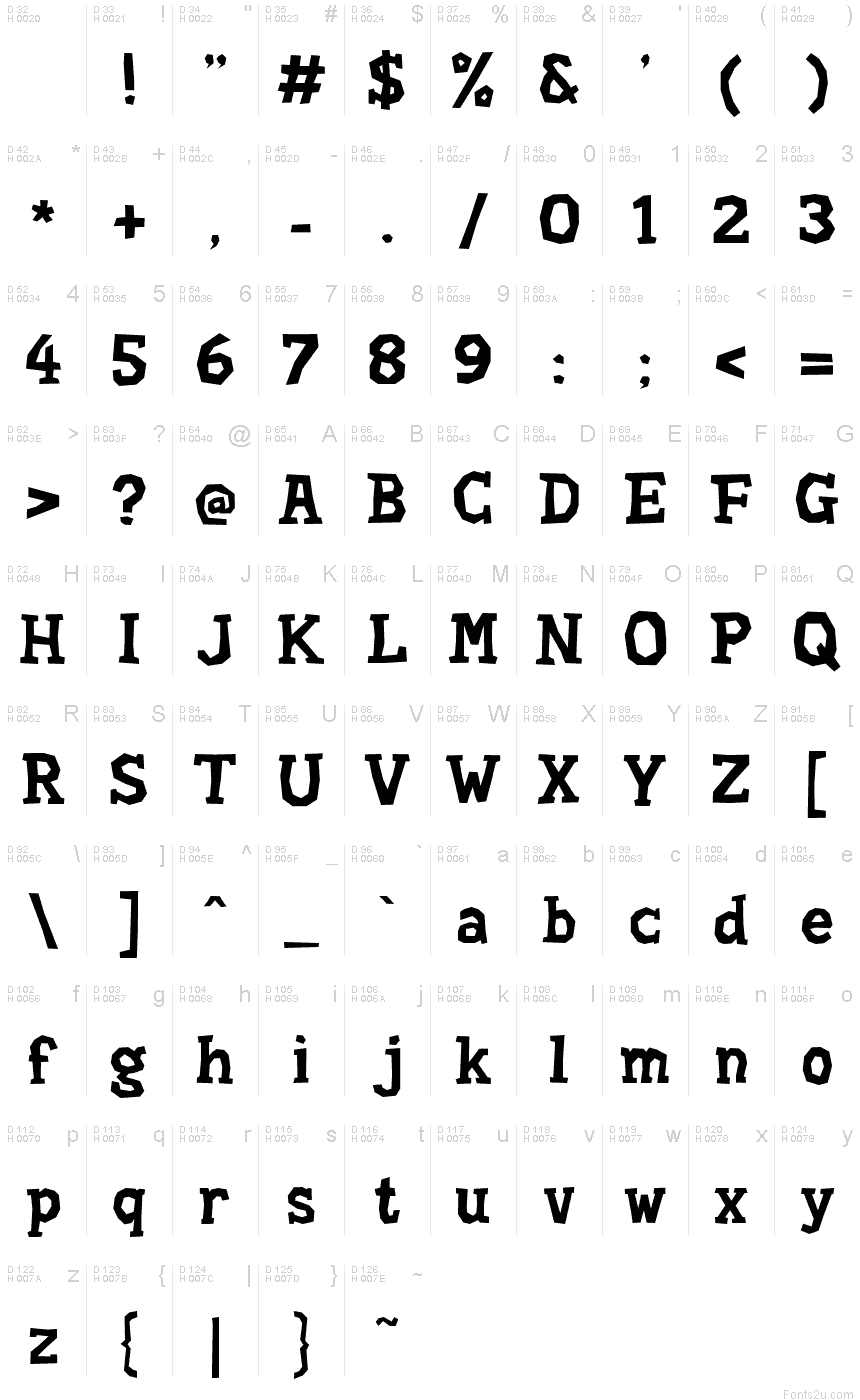
خط Hard Compound من Lefly هو خط عرض مجاني ومشوه، يتميز بمظهر خشن كأنه مقصوص من الورق المقوى، ويترك أثراً قوياً مثل الملصقات المصنوعة يدوياً. كل حرف يميل ويتأرجح قليلاً، مع حواف مربعة وضربات غير متساوية تبدو خاماً ومليئة بالحبر وغير مستقرة نوعاً ما، وكأنه تصميم تم تجميعه على عجل لحفل موسيقي تحت الأرض. إنه خط جريء وصاخب يلفت الأنظار فوراً، حتى بمجرد نظرة سريعة.
استخدم Hard Compound في المشاريع التي تتطلب طابعاً قوياً، مثل شعارات فرق البانك أو الميتال، عناوين أفلام الرعب، ملصقات الاحتجاج، المجلات المستقلة، أغلفة الألعاب، ورسومات البضائع الجريئة. يتألق هذا الخط المجاني عند استخدامه بحجم كبير وبتقارب كبير بين الحروف، لذا اجعله يبرز في العناوين وقم بإقرانه بخط بسيط بلا زوائد (Sans Serif) لأي نص إضافي.